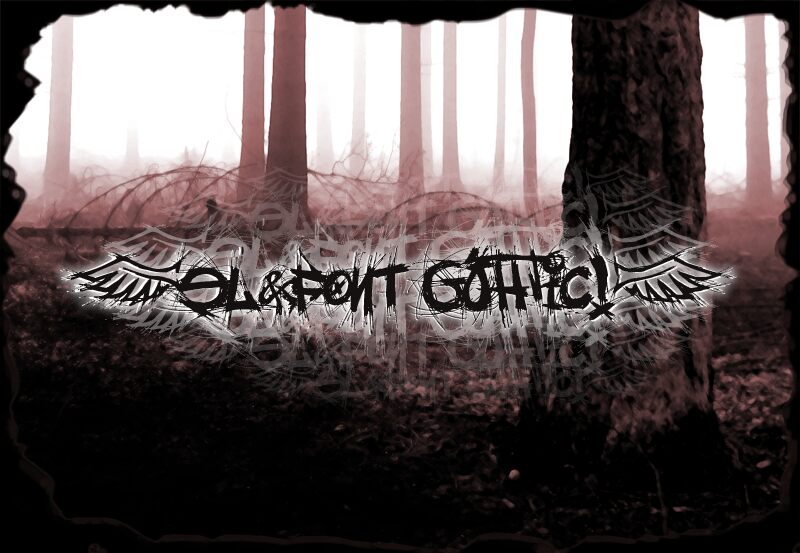
el&font gohtic!
El&font Gohtic! to darmowy krój display w stylu trash, który wygląda, jakby został wydrapany na ścianie potłuczonym szkłem. Szarpane kreski, tekstury pryskającego tuszu i dzikie, nierówne kąty nadają każdemu słowu frenetyczną, hałaśliwą energię, sprawiając wrażenie, jakby litery wibrowały na stronie. To surowy, niechlujny i bezkompromisowy krój – idealny, gdy chcesz, aby Twoja typografia była głośna, namacalna i odrobinę niebezpieczna.
El&font Gohtic! sprawia, że Twoje nagłówki wykrzykują z plakatów koncertowych, tytułów horrorów, undergroundowych zinów, grafik na deskorolki, okładek albumów i agresywnych postów w mediach społecznościowych. Ten darmowy font najlepiej prezentuje się w dużym rozmiarze, gdzie odpryski i plamy tuszu mogą naprawdę oddychać. W przypadku mniejszych podpisów lub tekstu głównego, połącz go z czystym krojem bezszeryfowym, aby zachować czytelność, pozwalając jednocześnie grunge'owym literom grać pierwsze skrzypce.